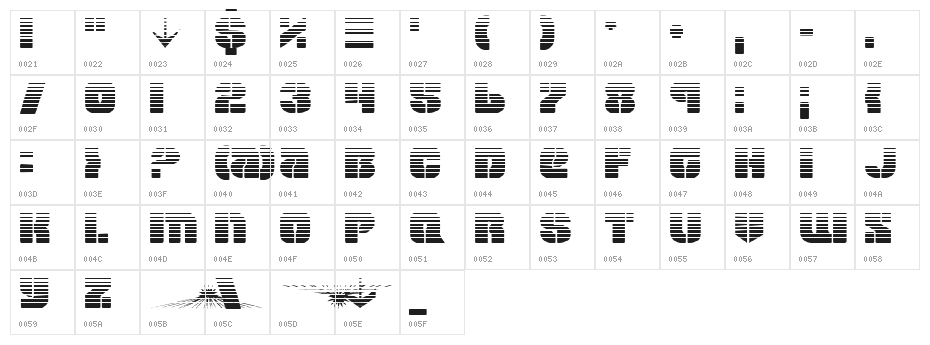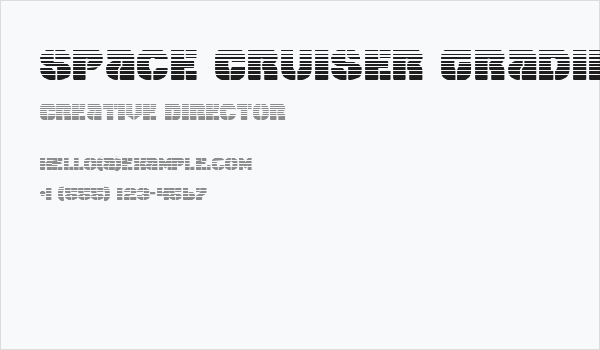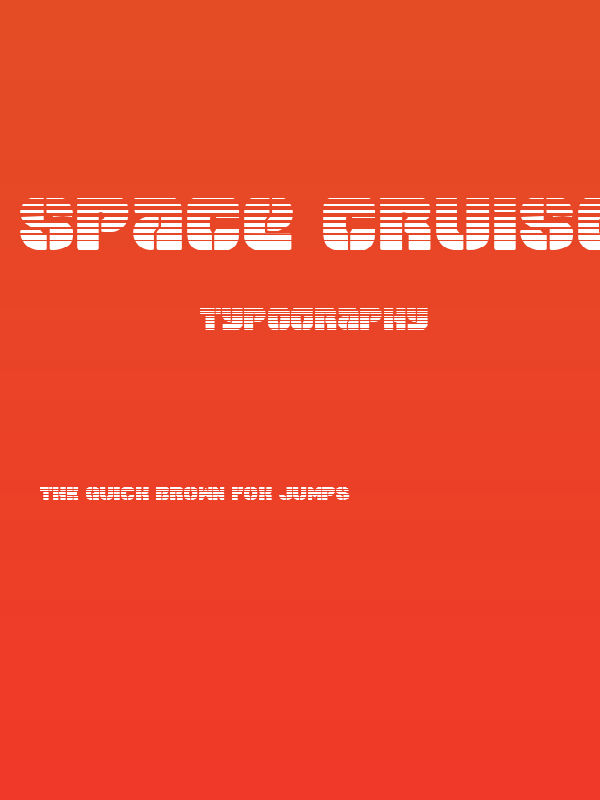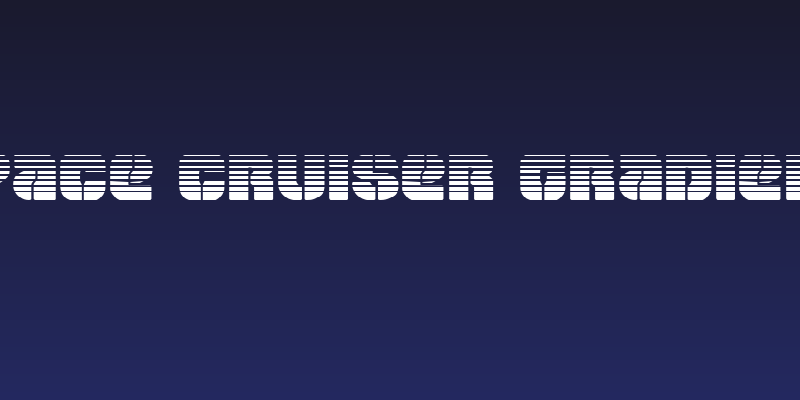
Space Cruiser Gradient Font
| Gewicht | Gradient |
| Kategorien | Decorative |
| Gesamtstil | Futuristic |
| Vorgeschlagene Projekte | Ideal for sci-fi movie posters, tech branding, video game titles, and futuristic event flyers. |